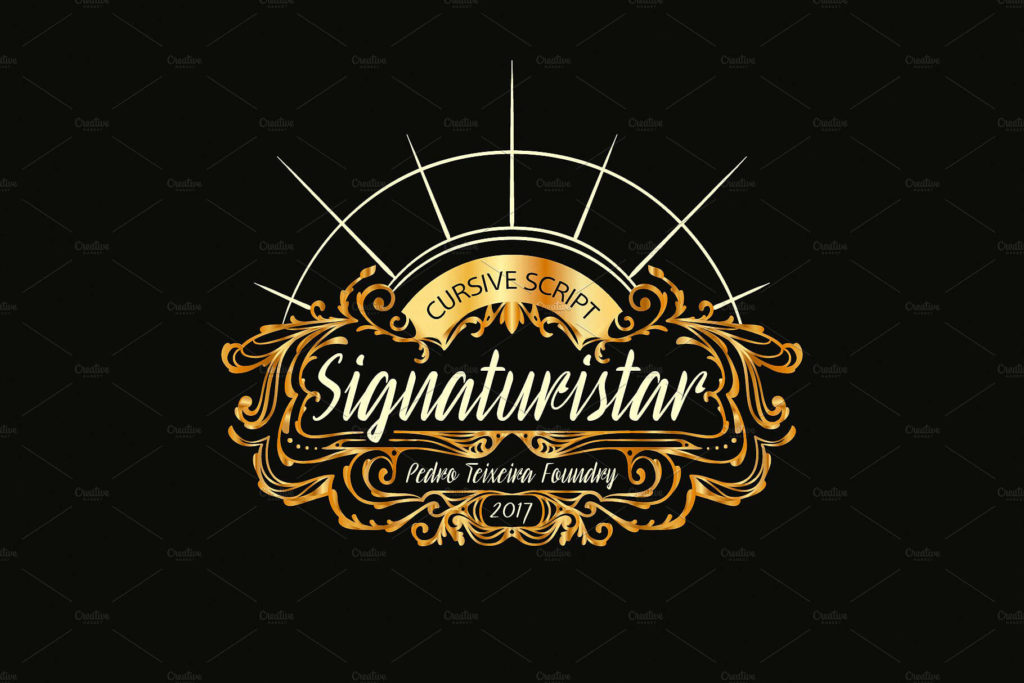
Шрифт Signaturistar
это выразительный ретро-курсивный шрифт от студии Pedro Teixeira Foundry. Он стилизован под рукописное начертание с характерными мазками кисти, создавая эффект энергичной подписи или автографа. Шрифт полностью поддерживает кириллицу и латиницу, включая расширенные наборы для европейских языков (турецкий, балтийские). Его динамичный рисунок букв и винтажный характер делают его идеальным инструментом для создания уникального визуального стиля в проектах с ноткой ностальгии